コピペできない“木”04「太さ」
文字の一体感を出すのに太さの調整は欠かせません。中心に来る「木」は横画の調整が多めで、一文字全体の横画の本数や強く見せるべき筆画を意識しながら太さを合わせていきます。逆に、木偏など縦長の「木」で様々な幅に対応するため調整するのは主に縦画の太さです。ハライについては、横に長いハライなら横画を目安に、縦に長いハライなら縦画を目安にしていますが、画数の多い漢字ではあえて細めにして混雑を回避することもあります。「木」は線が集まる部分の黒味が強くなりやすいため、他の要素よりも筆画を細めにしたりして一文字全体の黒味に合わせるのもよくある調整です。
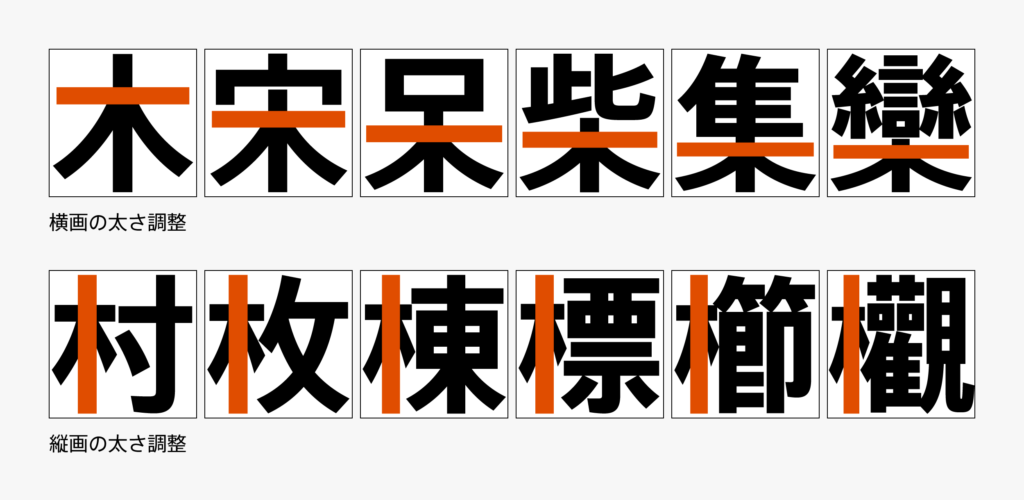
ここまで「木」が入る漢字の制作について紹介しました。他の部首に応用できるポイントもありましたが漢字の構成要素にはそれぞれ特有の注意点もあるので、フォントで一通りのグリフを作るためには他にも様々な調整が行われています。